ビジネス・資料向けフリーフォントをご紹介!
ビジネス文書やプレゼン資料において、フォントの選択は内容の伝わり方を大きく左右します。特に明朝体は、読みやすさと品位を兼ね備えた書体として、公式な場面での使用に適しています。報告書や企画書などの印刷物から、デジタル上での提案資料やホワイトペーパーまで、幅広いビジネスシーンで活躍します。
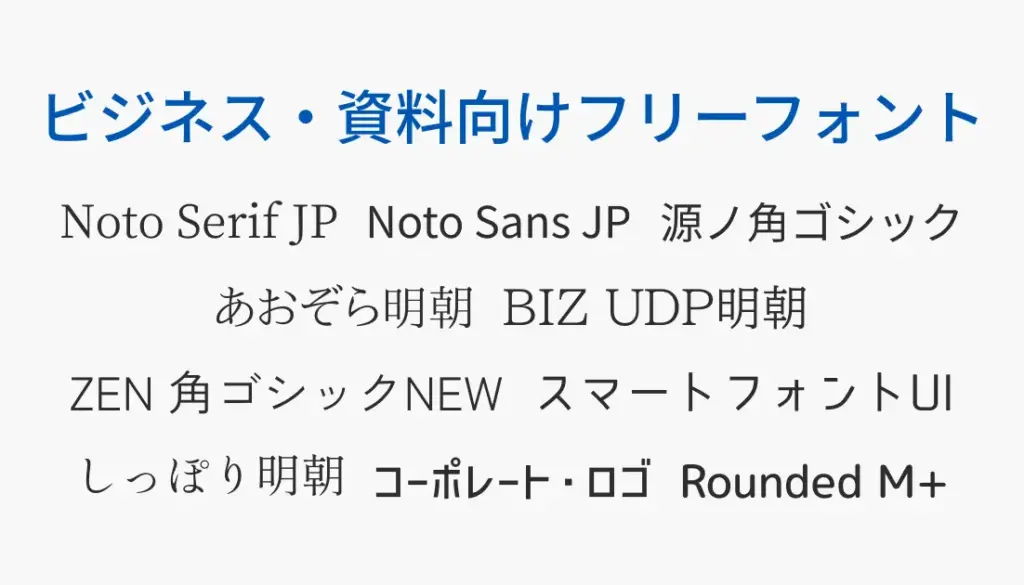
今回は、無料で利用でき、商用利用も可能なフォントの中から、ビジネス用途に適した10書体を厳選しました。正統派で安定感のあるものから、やわらかさを感じさせるもの、洗練されたモダンな印象を与えるものまで、それぞれの特徴や活用シーンをご紹介します。
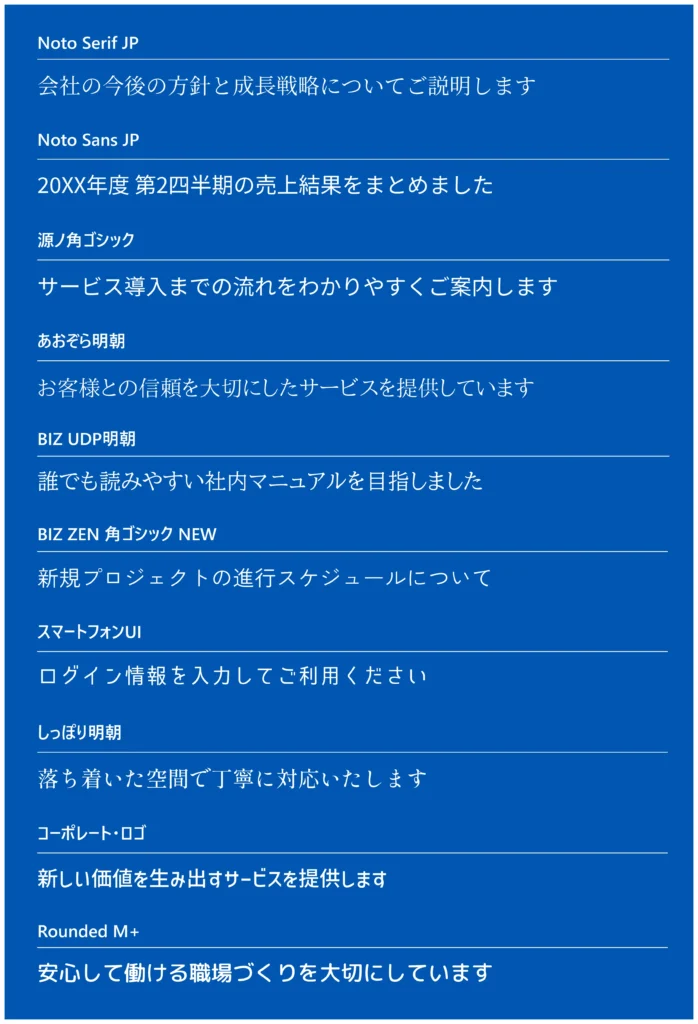
1. Noto Serif JP
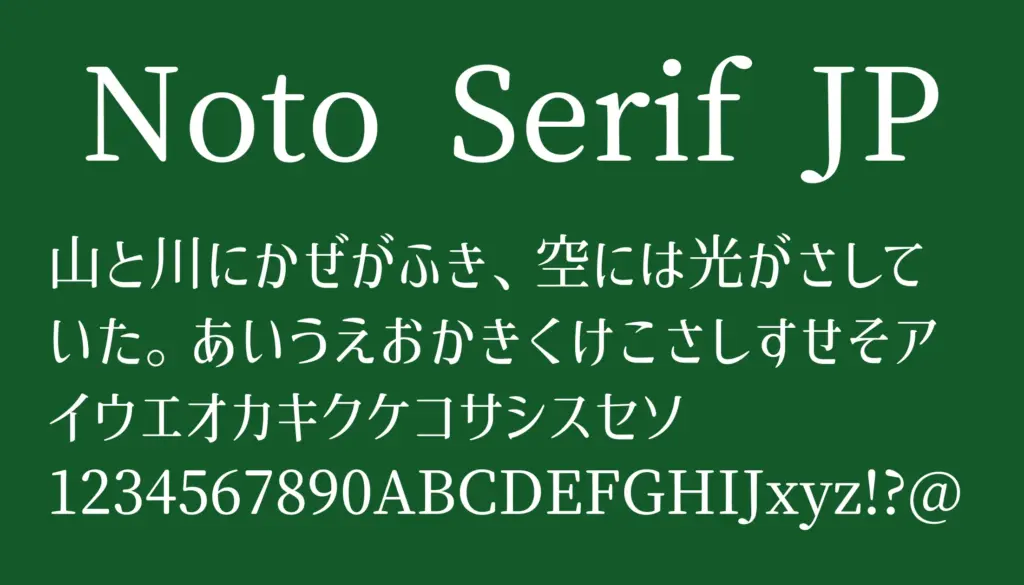
| 活用シーン例 | 報告書 / 論文 / ホワイトペーパー |
Googleが提供するオープンソース明朝体です。安定した可読性と美しい字形を備えており、ビジネス資料から論文まで幅広く安心してお使いいただけます。
2. Noto Sans JP
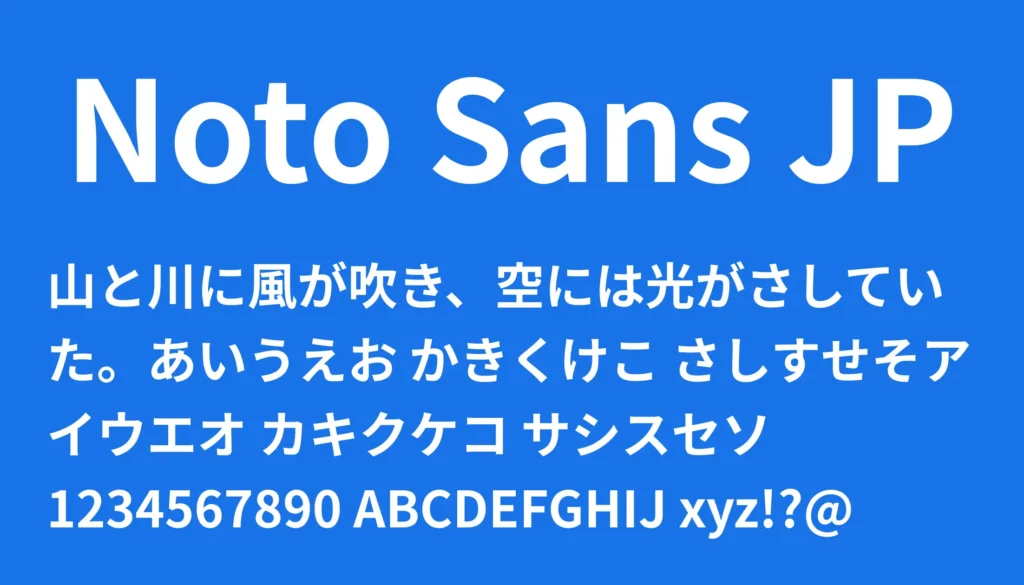
| 活用シーン例 | Web記事 / 提案資料 / プレゼン資料 |
モダンで視認性に優れたゴシック体です。画面表示でも崩れにくく、Webやスライド資料など、デジタル環境でも安心してご利用いただけます。
3. 源ノ角ゴシック
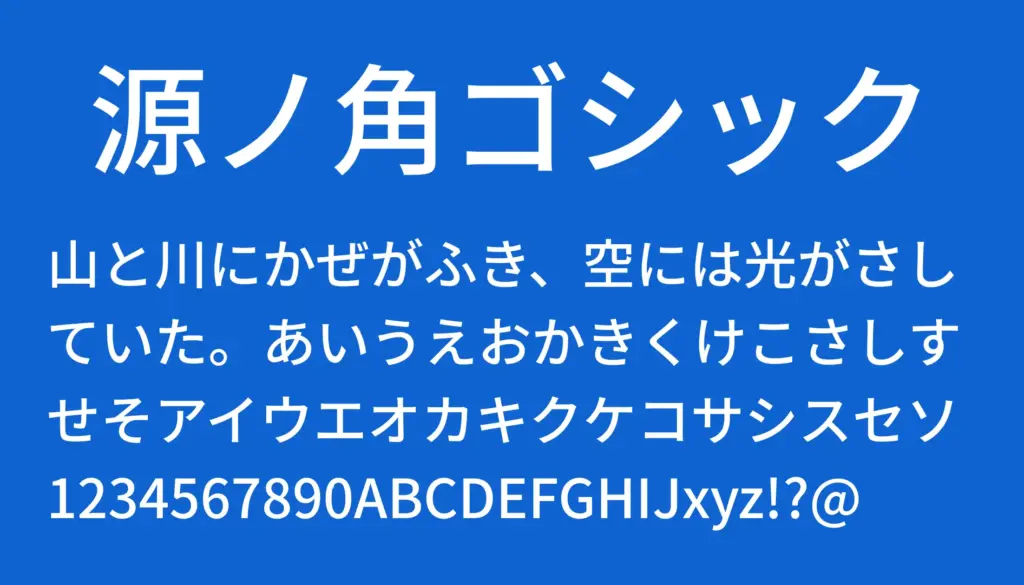
| 活用シーン例 | ビジネスレポート / 契約資料 / パンフレット |
AdobeとGoogleが共同開発したプロ仕様のゴシック体です。文字の安定感と信頼性が高いため、幅広いビジネス用途に適しています。
4. あおぞら明朝
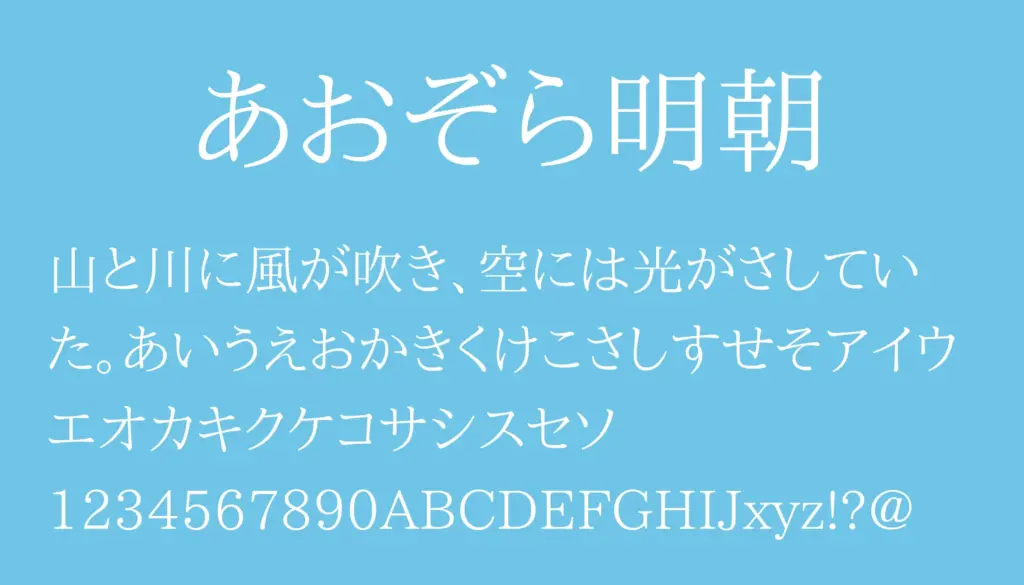
| 活用シーン例 | 研究資料 / 広報誌 / 会社案内 |
柔らかさと品格を兼ね備えた明朝体です。長文でも読みやすく、上品な印象を求める資料やデザインにぴったりです。
5. BIZ UDP明朝
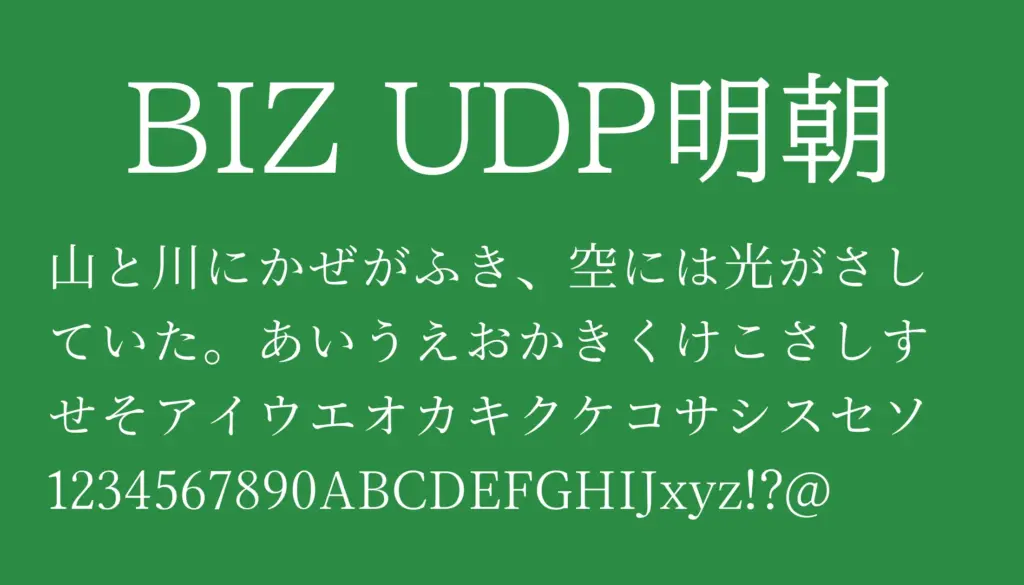
| 活用シーン例 | 官公庁資料 / 学校配布物 / マニュアル |
ユニバーサルデザインを考慮した明朝体です。誰にでも読みやすい設計になっており、公共性の高い資料におすすめです。
6. ZEN 角ゴシックNEW
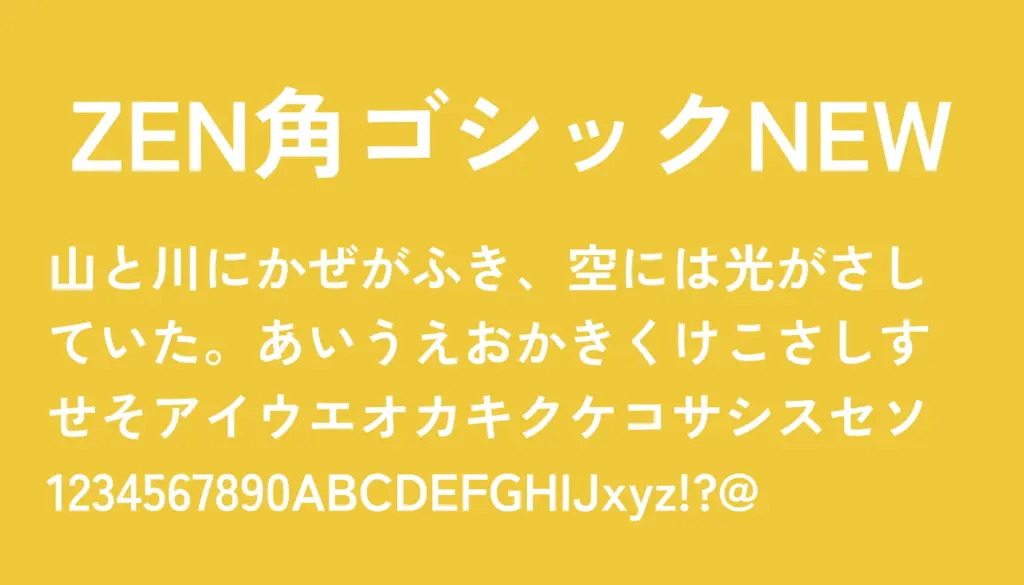
| 活用シーン例 | 企画書 / プレゼン資料 / グラフ説明 |
整った字形が特徴のゴシック体です。見出しや表組みで映えるため、企画書やプレゼン資料をより効果的に見せてくれます。
7. スマートフォントUI
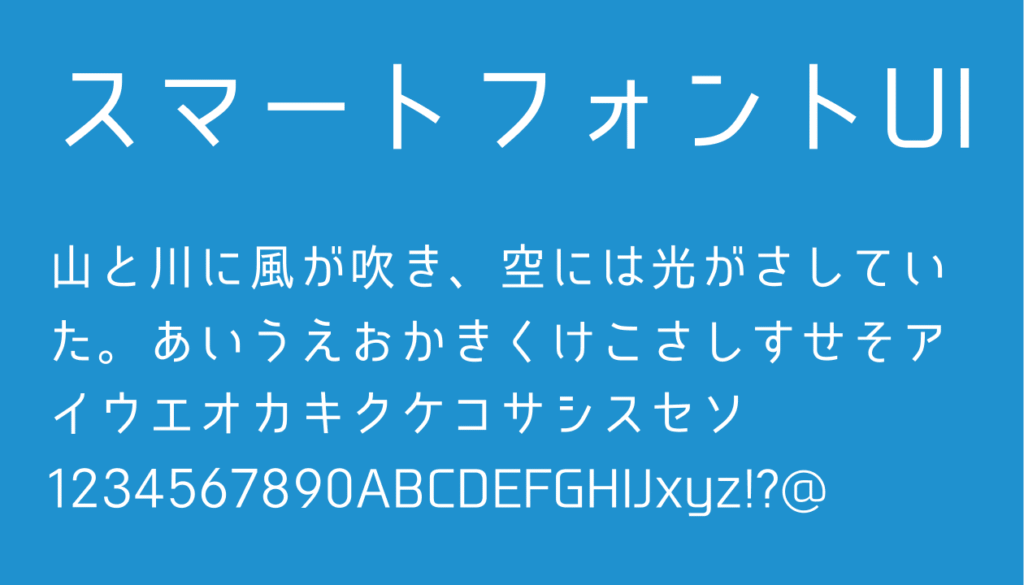
| 活用シーン例 | UI設計資料 / サービス紹介 / Webプレゼン |
細身でスマートなデザインのフォントです。デジタル表示に最適化されており、UI設計やモバイル画面での利用に向いています。
8. しっぽり明朝
| 活用シーン例 | 社内報 / 提案資料 / プレゼン資料 |
柔らかく落ち着いた雰囲気を持つ明朝体です。堅すぎない印象を与えられるため、提案資料や社内文書にも使いやすいです。
9. コーポレート・ロゴ
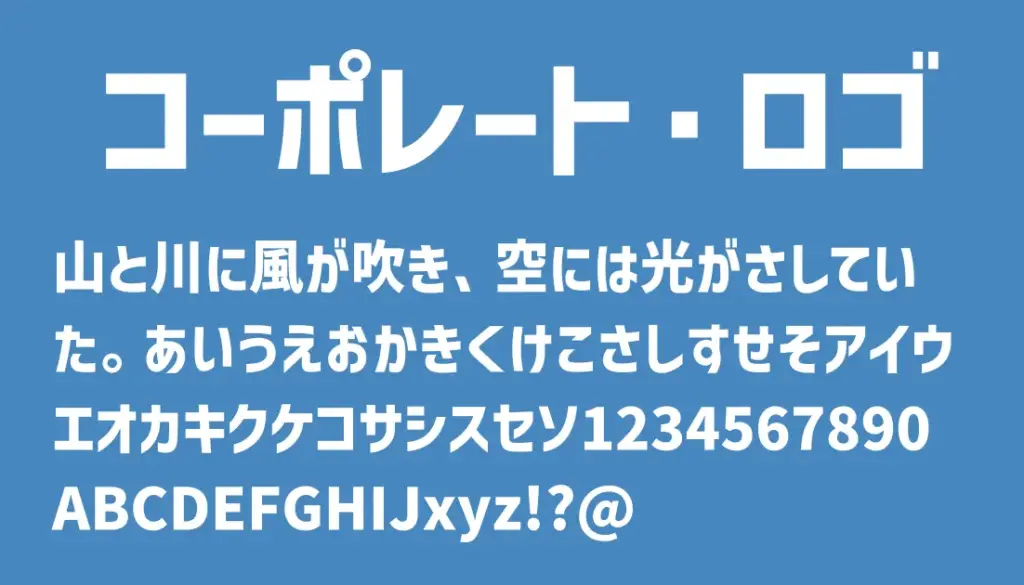
| 活用シーン例 | 提案書表紙 / パンフレット / ブランド資料 |
シンプルでモダンなロゴ用フォントです。資料の表紙やタイトルに使うと、洗練された印象を演出することができます。
10. Rounded M+
| 活用シーン例 | 教育資料 / 製品紹介 / 社内マニュアル |
丸みを帯びた親しみやすいゴシック体です。やわらかさと読みやすさを両立しており、教育や社内向けの資料に最適です。
まとめ